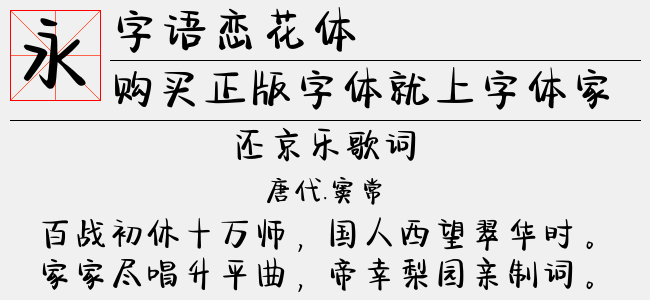
字语恋花体(5.09 MTTF中文字体下载)
字语恋花体 字体大小5.09 M,包含了6763个汉字以及附加其他英文字体和阿拉伯数字,属于字语字库。字语恋花体(TTF)可以免费下载,商业用途请自行购买版权,它的特征就是个性,标题,海报,卡通,采用安装嵌入的安装方式,支持符号拉丁文日文中文等语言
字体名称:字语恋花体